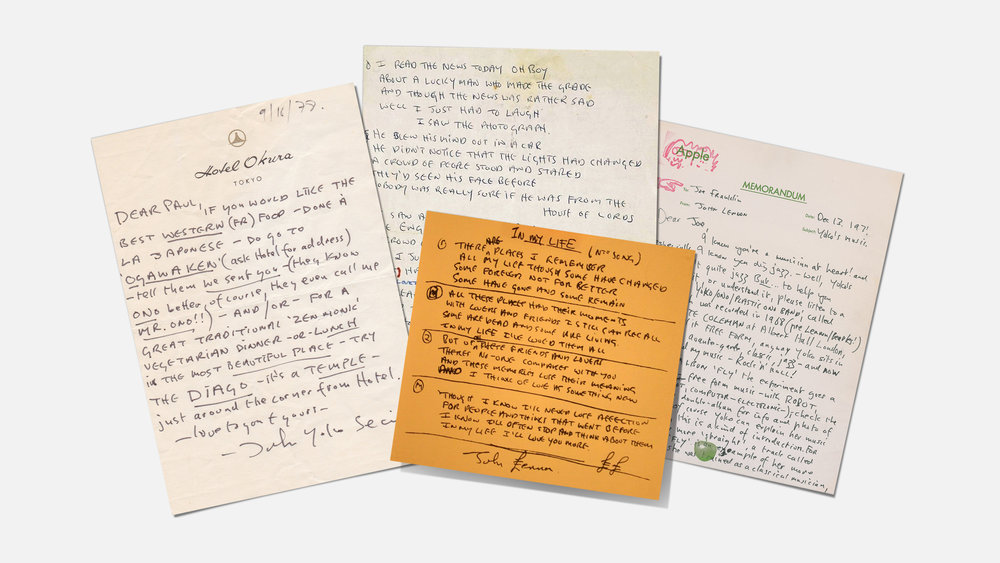
Quanti di noi vorrebbero avere una bella calligrafia. Dallo studio di come scriviamo si capiscono molte cose del nostro carattere poi. E come scrivevano gli artisti più famosi contemporanei? Ad esempio, com’era la calligrafia di David Bowie o di John Lennon
Da oggi ci pensa Songwriter’s Fonts (www.songwritersfonts.com), un progetto che permette di scaricare gratuitamente 4 font che ricalcano la calligrafia di alcuni fra i principali cantanti degli ultimi anni.
“Scrivete canzoni come quelli che vi hanno ispirato” è il payoff del sito, curato dai designer francesi Nicolas Damiens e Julien Sans, i quali aggiungono che “scrivere canzoni con la grafia di compositori influenti aiuta lo sviluppo dell’immaginazione”. Bellissimi gli esempi di lettere e appunti scritti a mano, oltre che di Bowie e Lennon, anche di Kurt Cobain, Leonard Cohen e Serge Gainsburg.